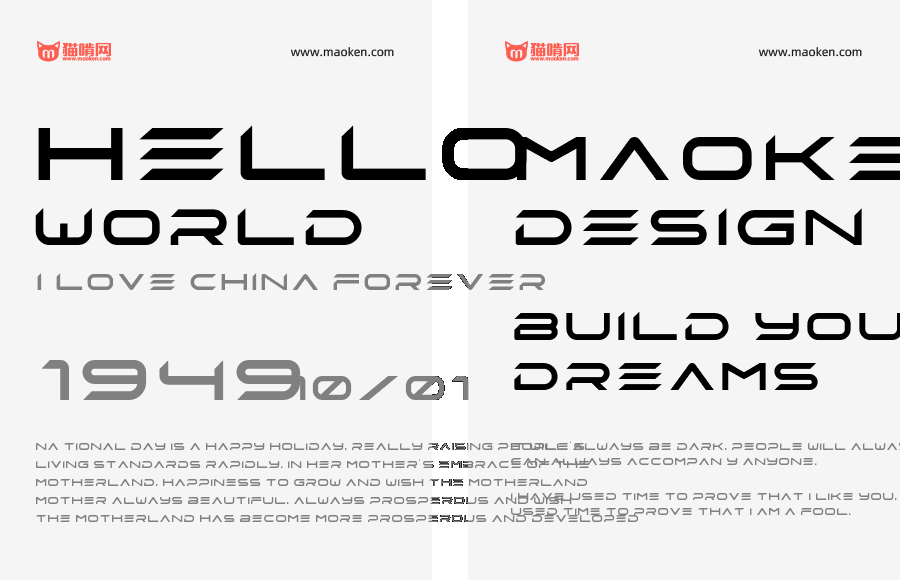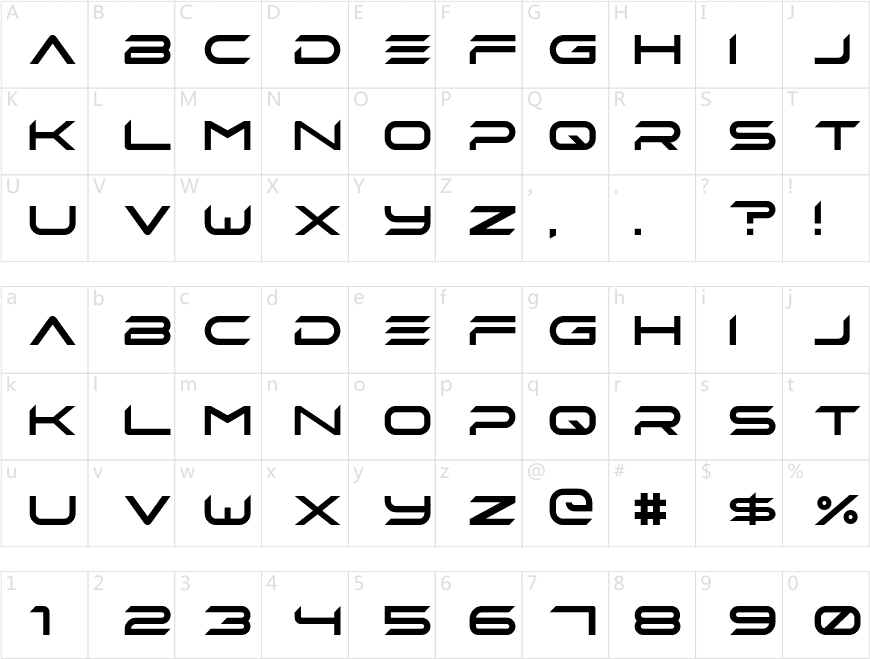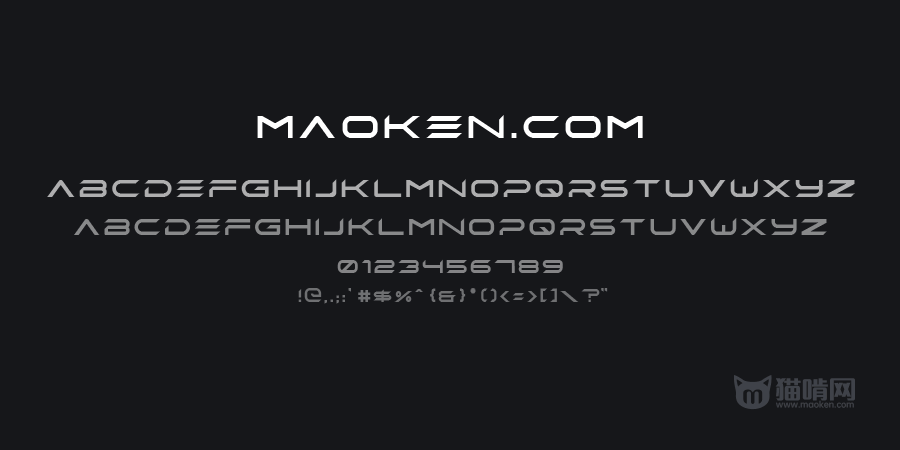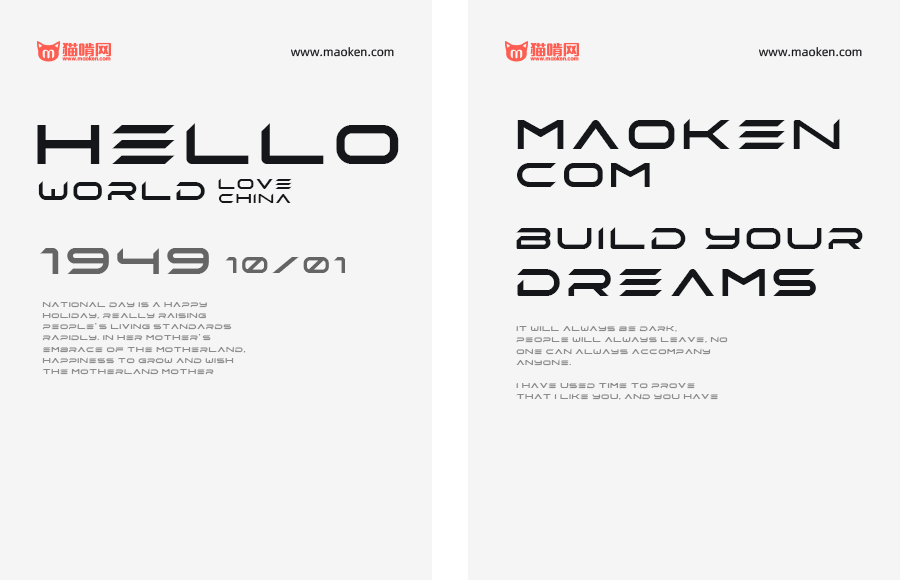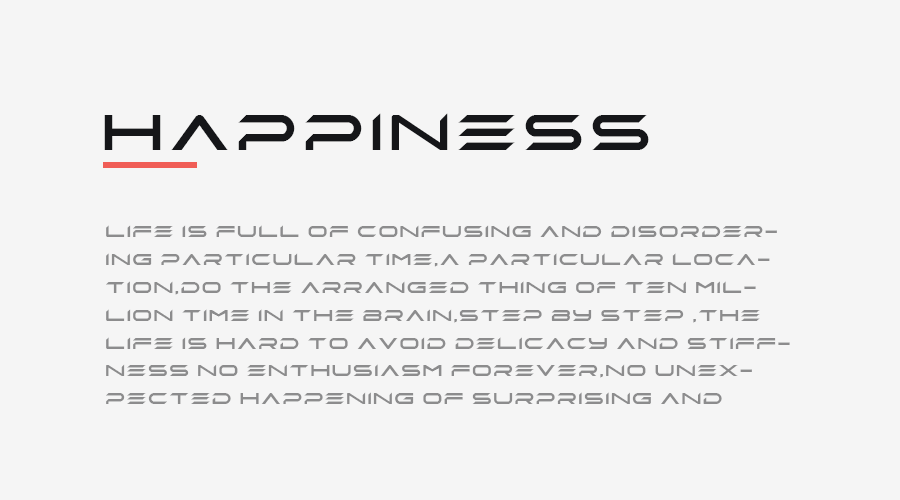
EDIX
字体作者:Dumpatom (中国) 字体字重:1个
EDIX是中国上海的设计师Dumpatom创作的一款超酷的英文字体,该字体的名称是提取了几个关键词的首字母即:进化(Evolution) 、设计(Design) 、创新(Innovate) 和高可复制性( Xerox)作为字体的名称。
该字体具有以下特点:
A.黄金比例中的极致美学
文字以简化为重点,所以细节和空间是影响美学的重要因素。由于个体的字母没有过多需要使用的元素,因此每个字符都需要做到极致。干净、简单、漂亮。是我对每个字符的基本要求,所以在字符表现结构上引用了著名的“黄金比例”,即在一个“黄金矩形”中创造字符。正是由于每个字符遵循美学-致性,所以在实际应用时都能获得良好的视觉效果。
B.独特的缺角特征
当说到科技和未来,人们会联想到稳健,有活力,发展迅猛。所以我想设计出体现这些特点的字体,最终能够应用于品牌及各种宣传标题上,以统- -品牌理念及精神。在保证字符美感的基础上做切角处理,其所呈现出的速度感,由速度感所产生的科技感,可以很好的反映使用者领导时代潮流的想法。
C.聪明的圆角处理
传统书写中,中文的书写- -直限定在田字格中,而拉丁文的书写一-直在尝试突破界限。如何让拉丁字符限制在黄金矩形中且获得美感上的统- -,成为了这次字体设计中的最大难点。所以我在找一些形象又与现代感结合的图形时,希望借助圆角来弱化字符本身的尖锐感,例如A N V Z这样典型的有角字母。而像C E S P这样本身并无有角特征的字母,则保持他们基础字形的同时融入切角元素使其具有洒脱的观感,加强了字母的节奏感。